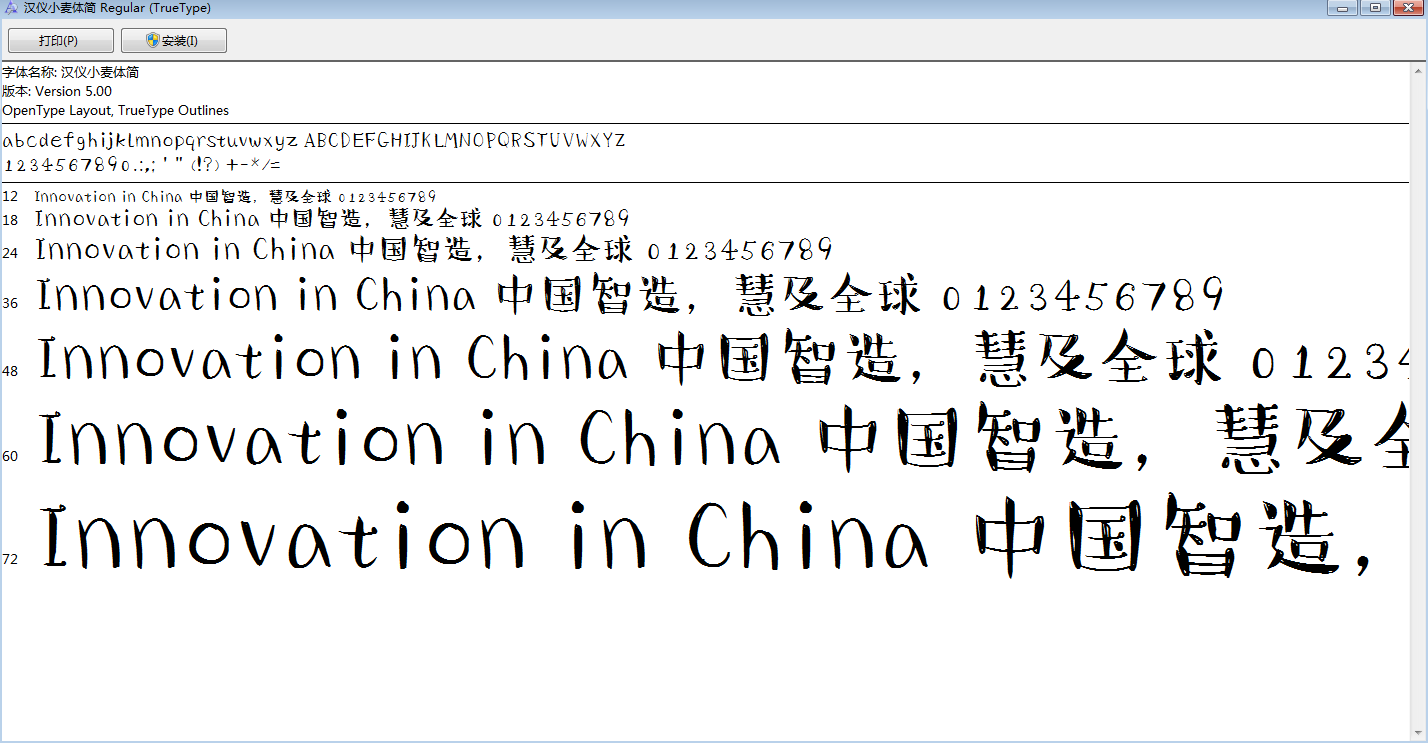
hyxiaomaitij-gbpc-euc-h字體就是一款ttf格式的漢儀小麥體,該字體字形清新,筆畫簡(jiǎn)單,帶有手寫體風(fēng)格,適用于一些休閑假期主題的海報(bào)或廣告設(shè)計(jì),歡迎需要的朋友下載使用!
hyxiaomaitij是一款具有漫畫風(fēng)格的可愛字體,漢儀小麥體的筆畫的粗細(xì)變化,有漫畫一樣輕松流動(dòng)的感覺,令人感覺到舒適,